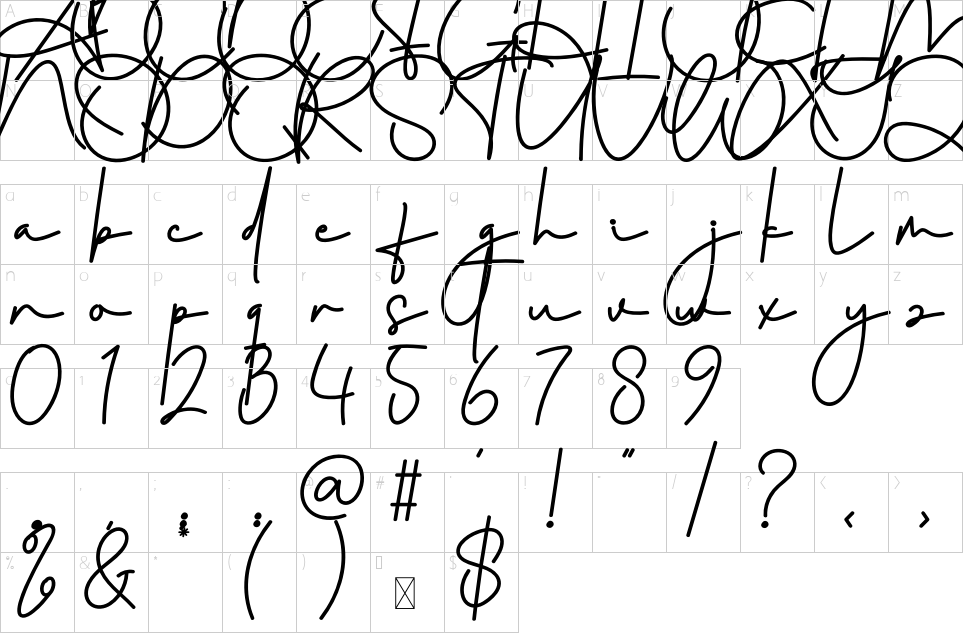
December Christmas Font – Download Grátis
Esta fonte chamada “December Christmas Font” está disponível gratuitamente para download tanto para Windows quanto Mac. Foi criada pelo designer scratchones e tem sido baixada 285 vezes. Esta elegante fonte é perfeita para decorações natalinas ou qualquer projeto que deseje uma aparição alegre e festiva durante o mês de dezembro. Seja você um decorador, criador de cards ou até mesmo alguém que apenas quer adicionar um toque especial ao calendário do seu site, esta fonte certamente vai se encaixar perfeitamente em seus projetos, deixando-os repletos de festa e luz natalinas. Não hesite em dar uma olhada para personalizar suas próximas criações.